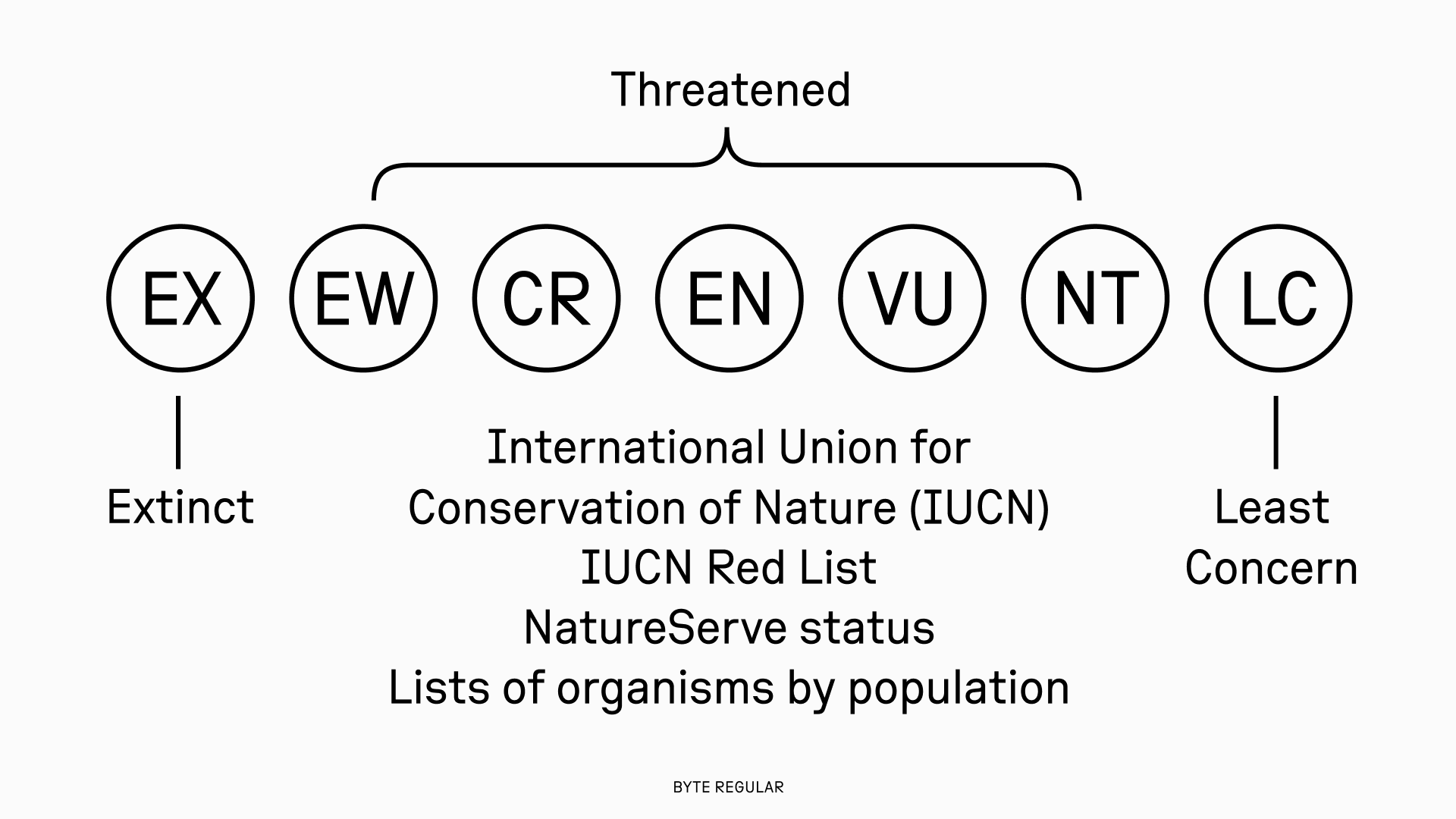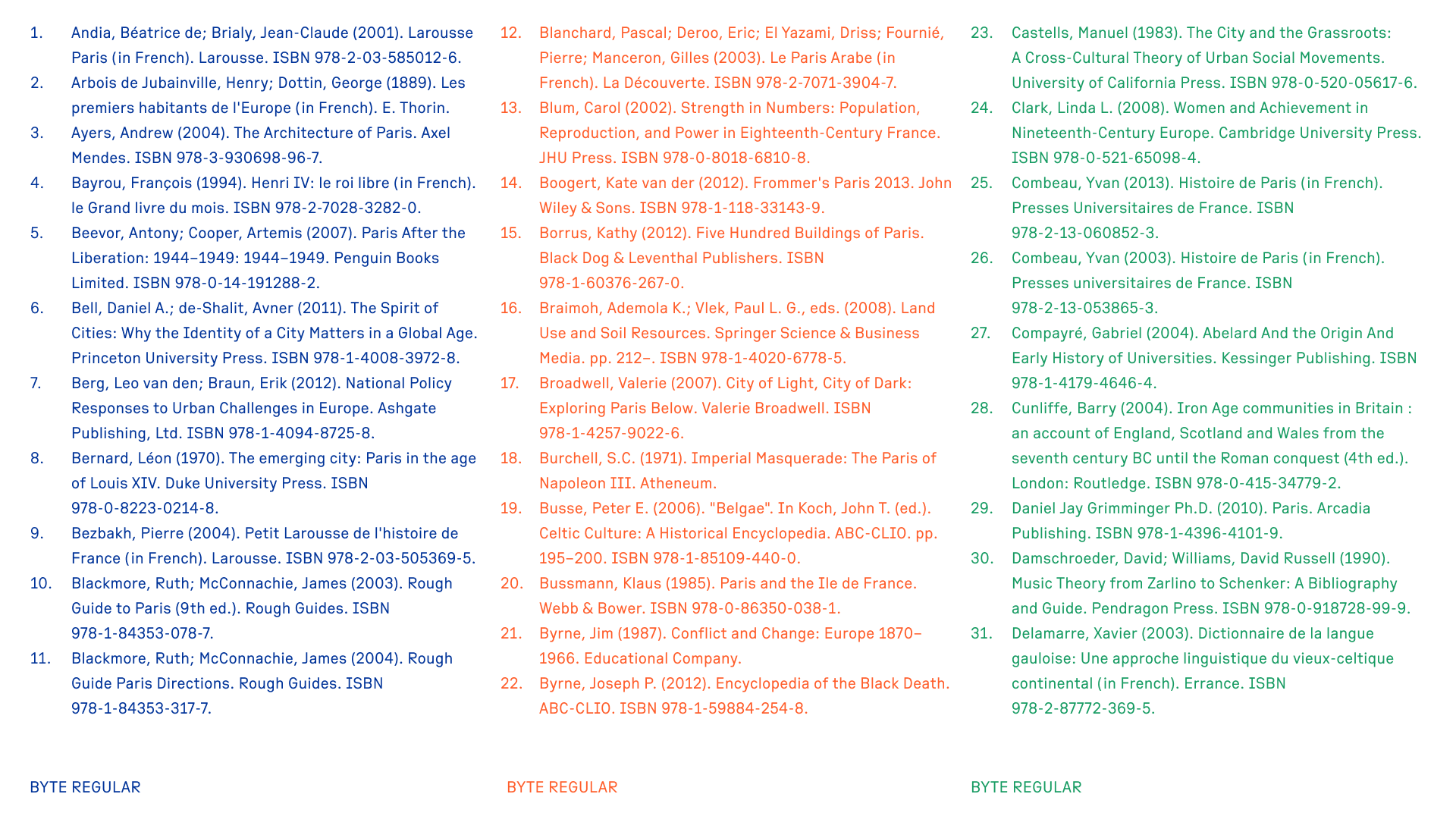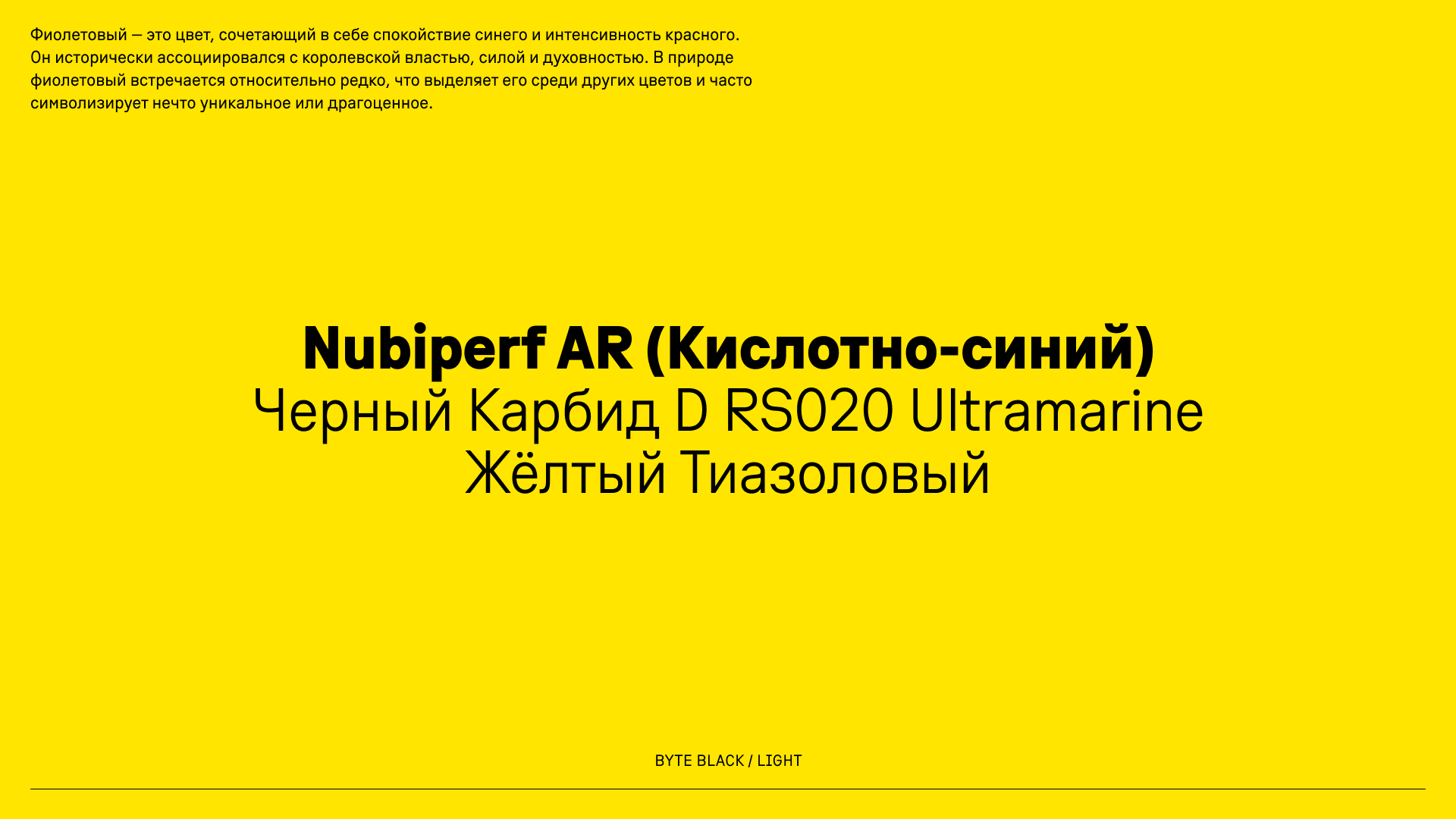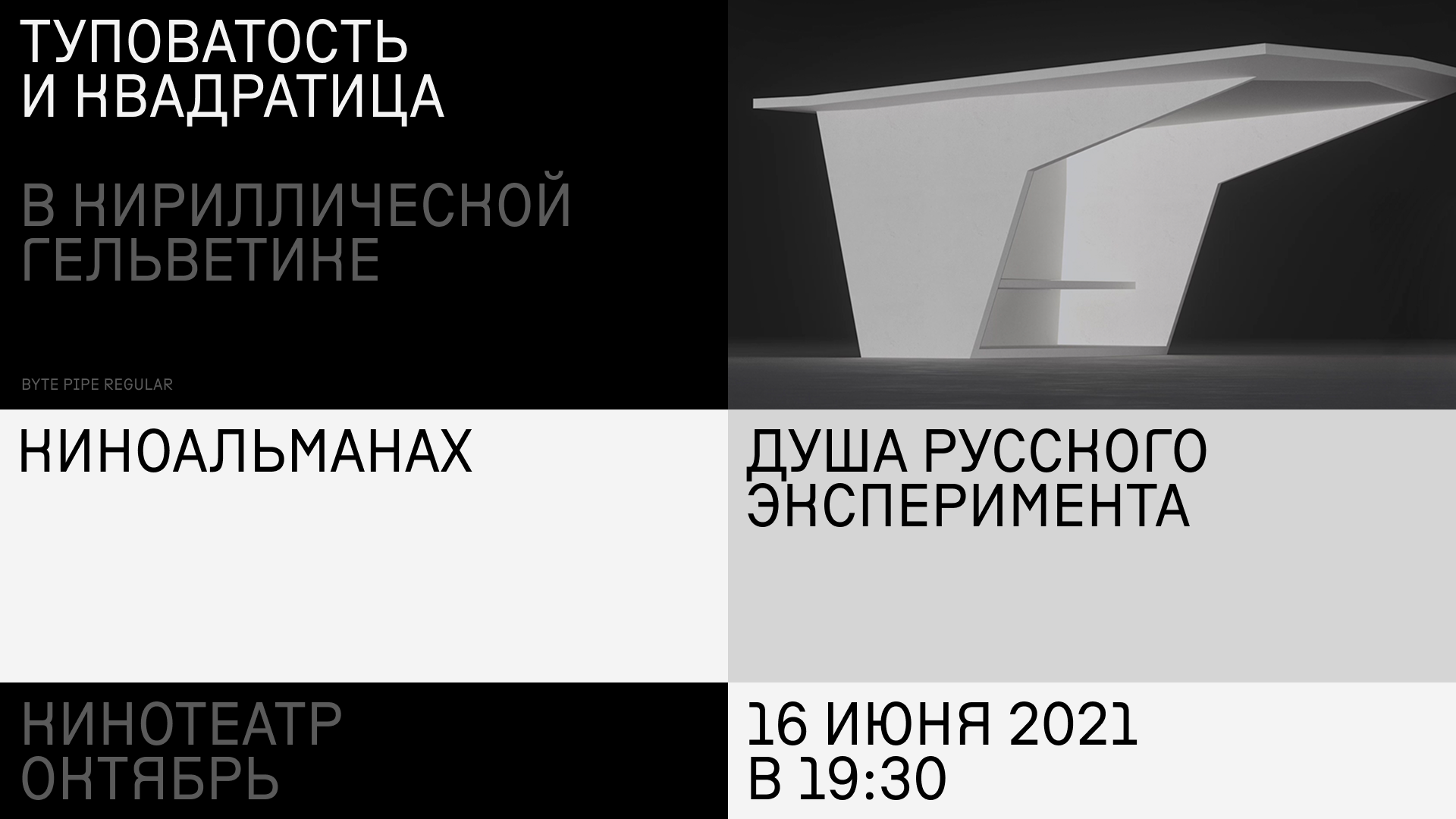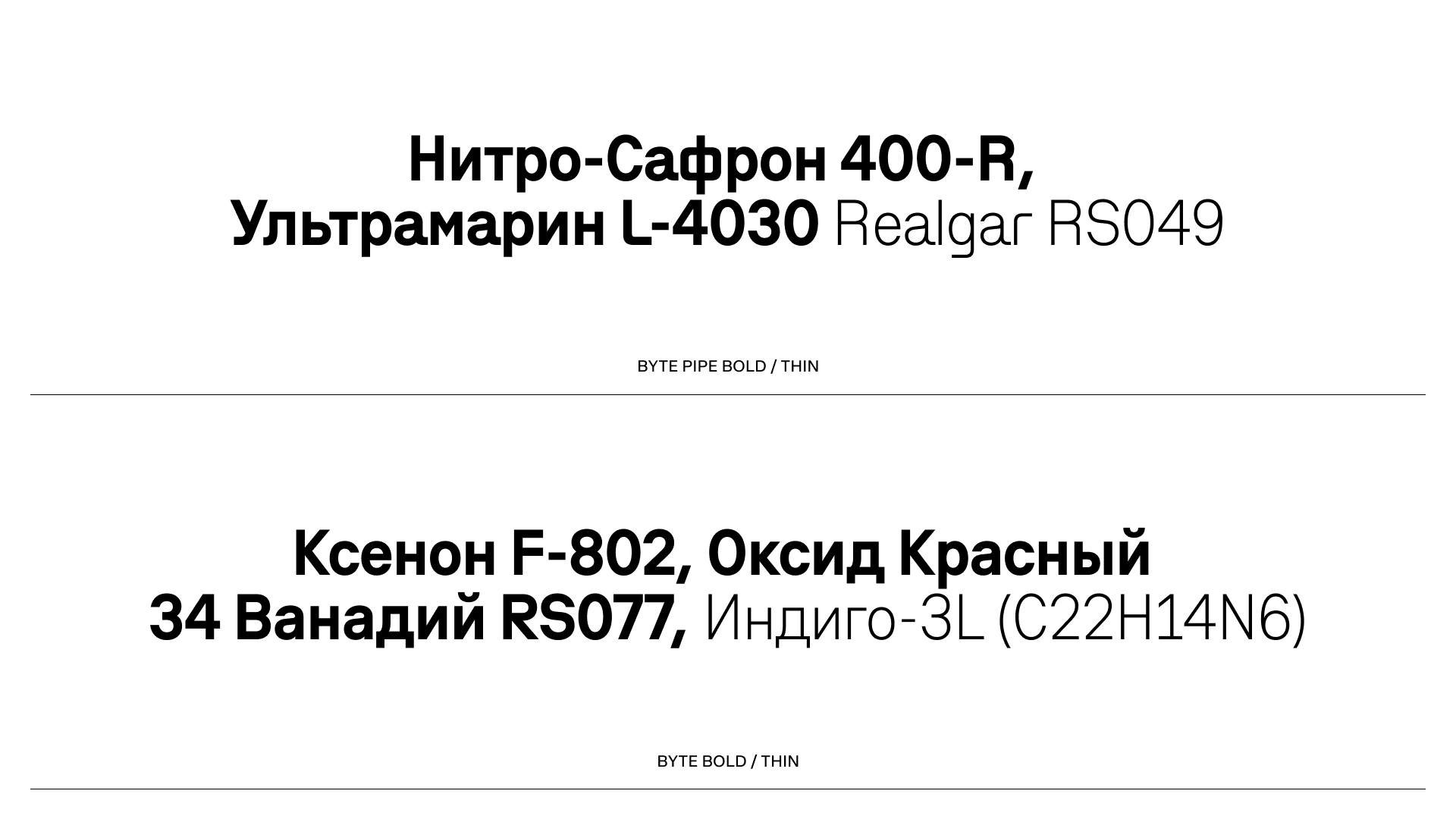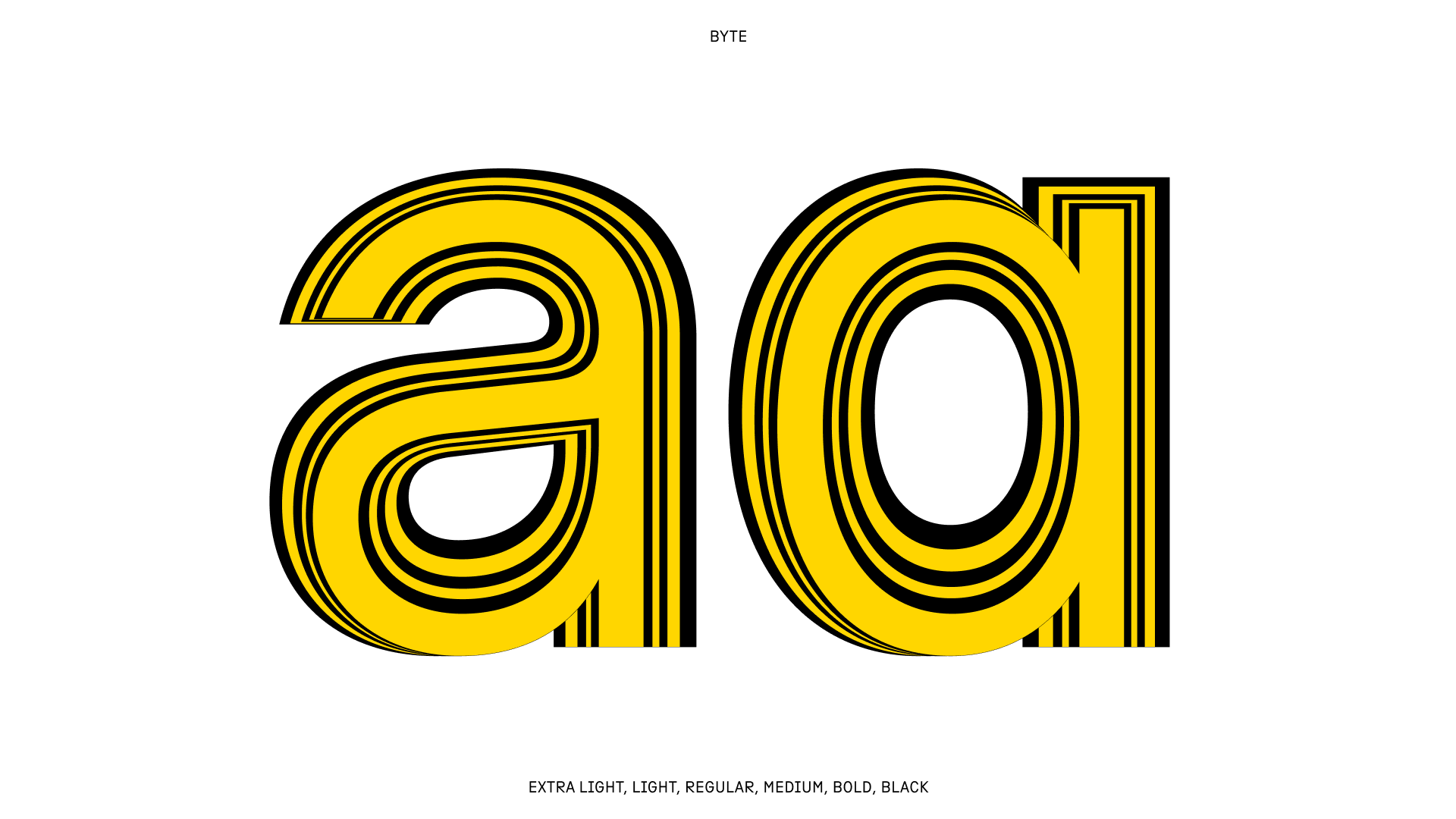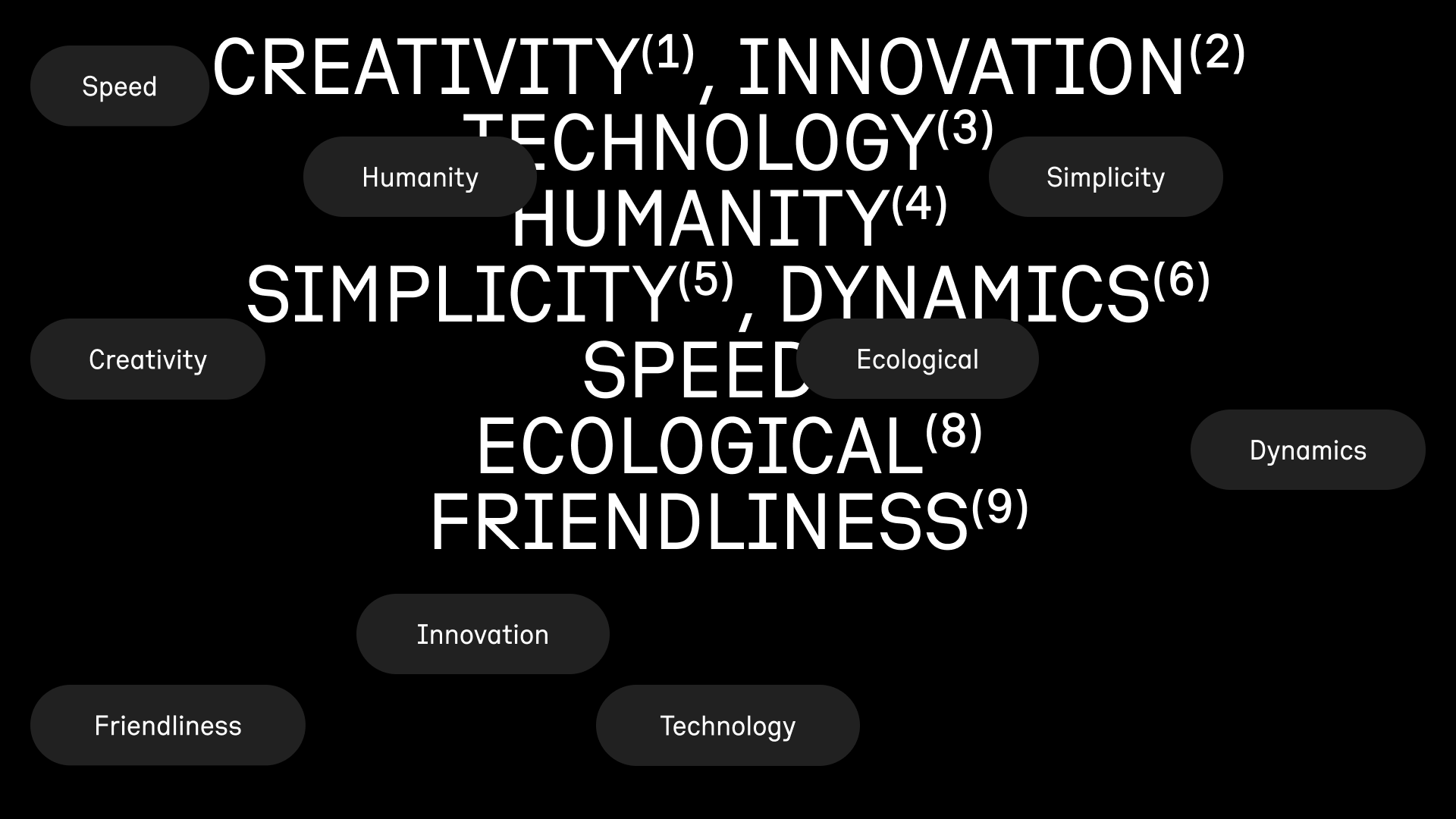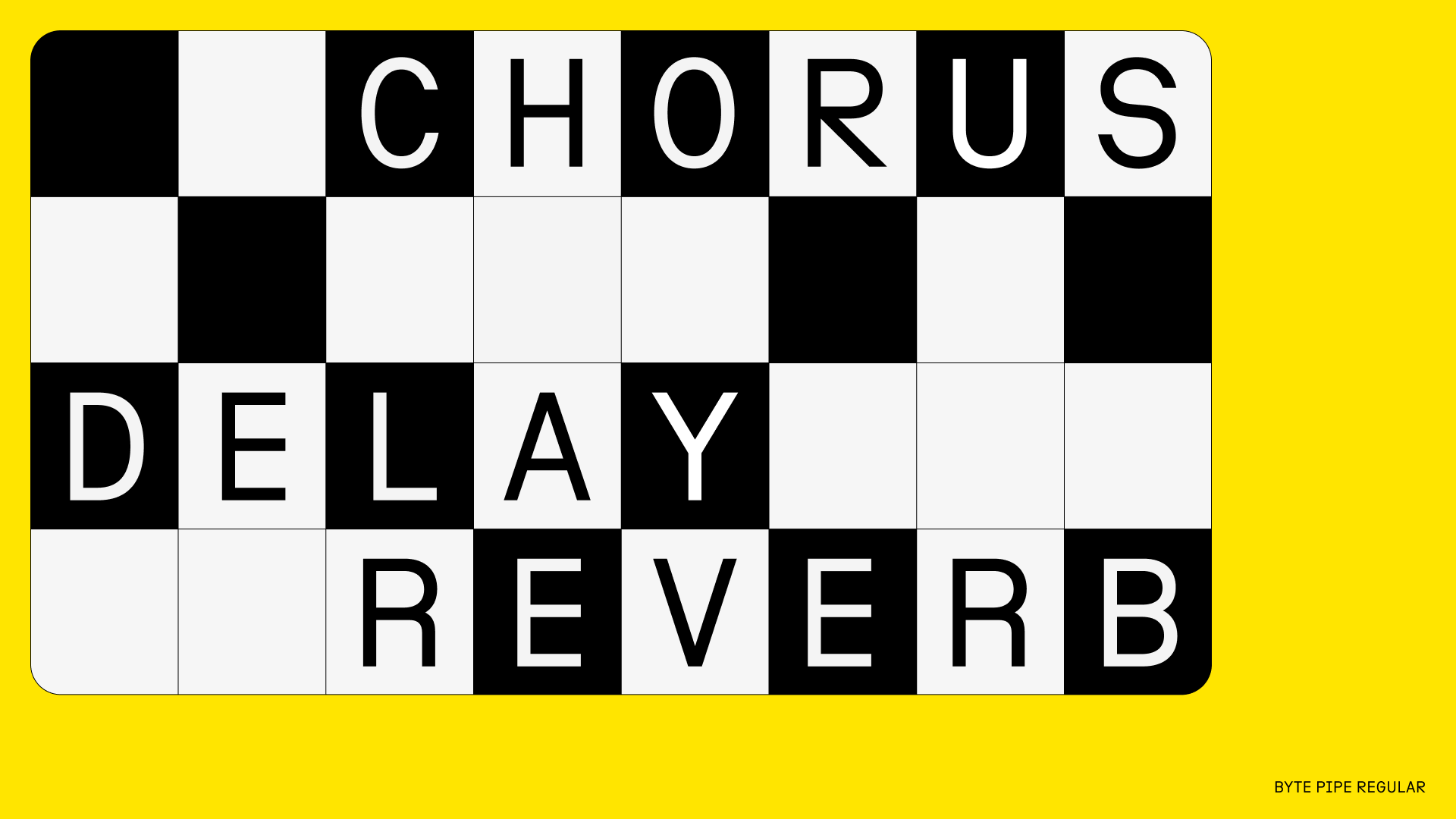
Byte Typeface
Пластика шрифта Byte вдохновлена темой кибербезопасности. Его характер формировался на основе собирательного образа моноширинных шрифтов, используемых для написания программного кода. Это наследие отразилось в базовых характеристиках: сближенные и зауженные пропорции, отсутствие контраста и свободный спейсинг. Такой набор параметров формирует технологичный образ с цифровым оттенком.
В шрифте предусмотрен альтернативный набор букв, смещающий интонацию от технологичности в сторону брутальности и эксцентричности. Радикальные решения отдельных графем позволяют создавать яркие типографические высказывания в крупном размере.